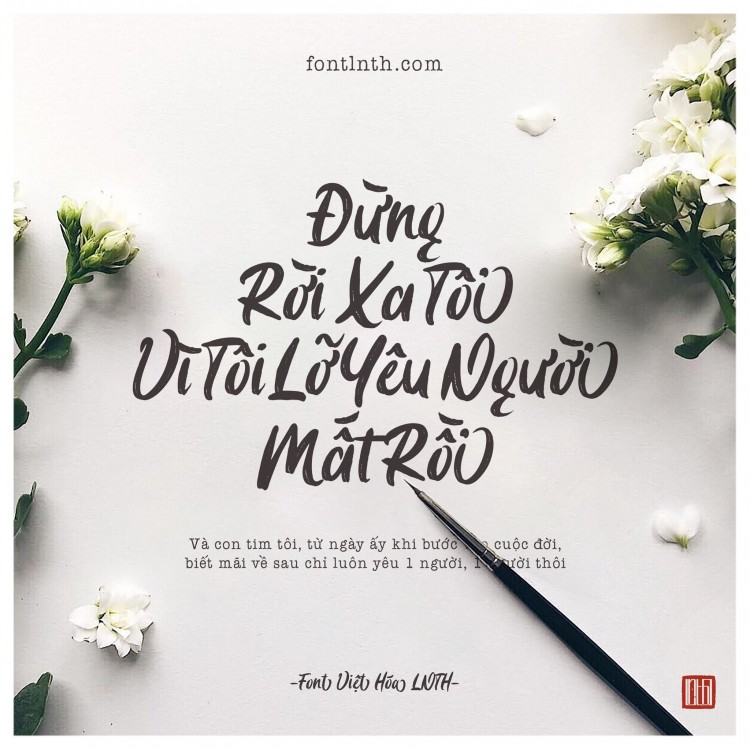
Font việt hóa LNTH Cabron
Giới thiệu về Font việt hóa LNTH Cabron
Trong thế giới đồ họa hiện đại, việc lựa chọn một bộ Font Miễn Phí chất lượng đóng vai trò then chốt tạo nên sự thành công cho tác phẩm. Font việt hóa LNTH Cabron là một bộ phông chữ độc đáo, mang phong cách mạnh mẽ nhưng không kém phần tinh tế. Được phát triển dựa trên cảm hứng từ những đường nét hiện đại, bộ font này đã được đội ngũ LNTH việt hóa tỉ mỉ, giúp các nhà thiết kế tại Việt Nam dễ dàng sử dụng mà không lo lỗi gõ dấu tiếng Việt. Đây là lựa chọn hoàn hảo cho những ai đang tìm kiếm sự phá cách trong trình bày văn bản.
Ưu điểm nổi bật của Font việt hóa LNTH Cabron
Thiết kế hiện đại và linh hoạt
Font việt hóa LNTH Cabron sở hữu các đường nét dứt khoát, độ tương phản vừa phải, giúp nội dung hiển thị rõ ràng trên cả thiết bị số và bản in. Kiểu dáng này cực kỳ phù hợp cho các dự án thiết kế logo, tiêu đề tạp chí hoặc bao bì sản phẩm cao cấp. Với bộ ký tự đầy đủ, bạn có thể tự do sáng tạo các biểu mẫu giáo dục hay poster sự kiện nhà trường sinh động.
Tương thích cao với phần mềm đồ họa
Cách ứng dụng Font việt hóa LNTH Cabron hiệu quả
Để phát huy tối đa vẻ đẹp của Font việt hóa LNTH Cabron, bạn nên kết hợp nó với các màu sắc tối giản hoặc tông màu trung tính. Trong môi trường học đường, font chữ này thường được dùng làm tiêu đề cho các slide thuyết trình để thu hút sự chú ý của học sinh. Sự cân đối giữa các nét chữ tạo cảm giác chuyên nghiệp, dễ tiếp cận cho người xem.
Kết luận về bộ font chất lượng